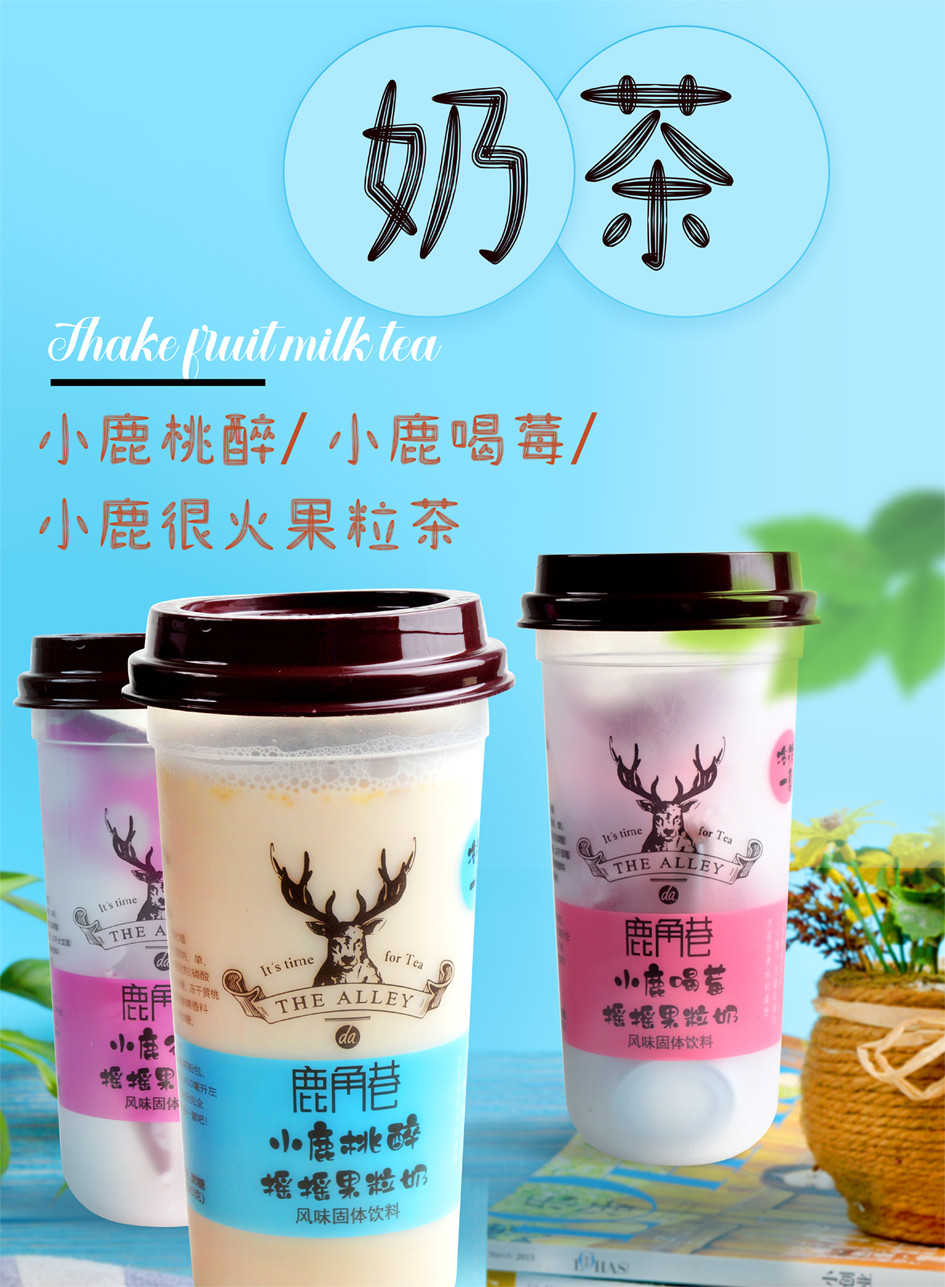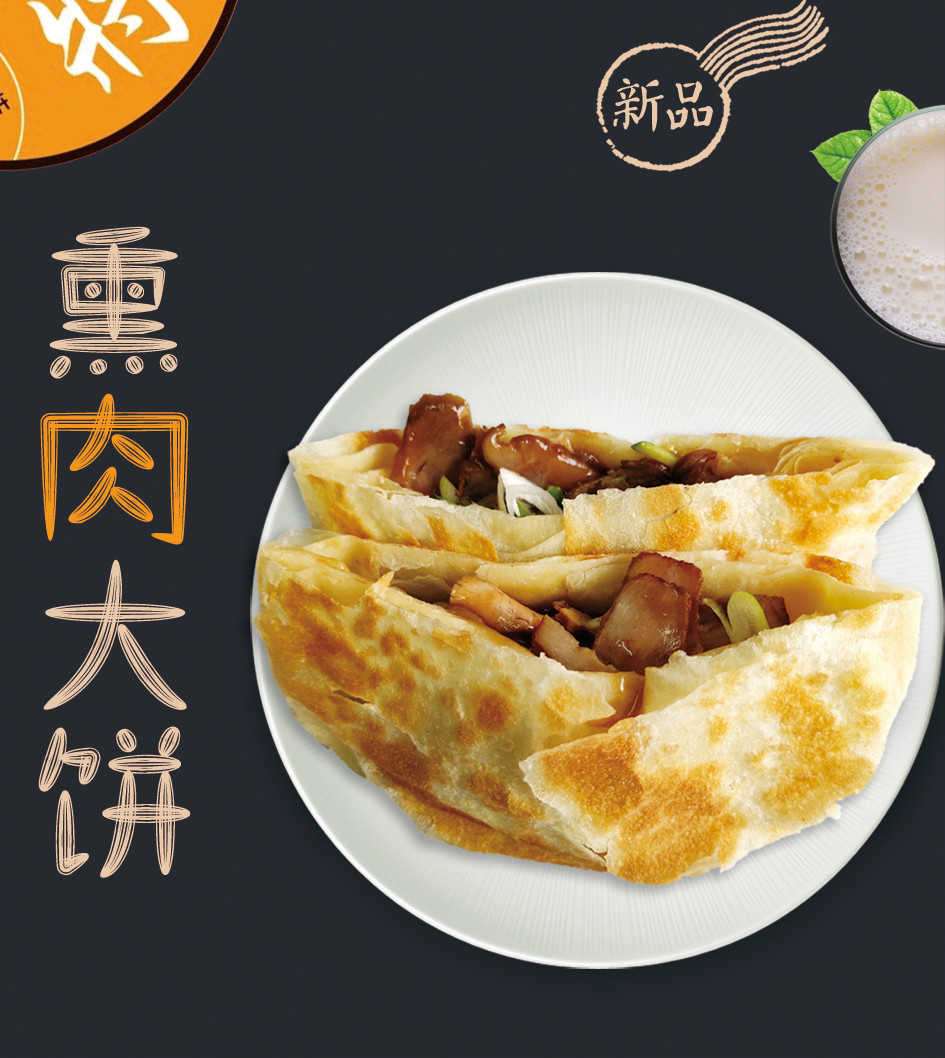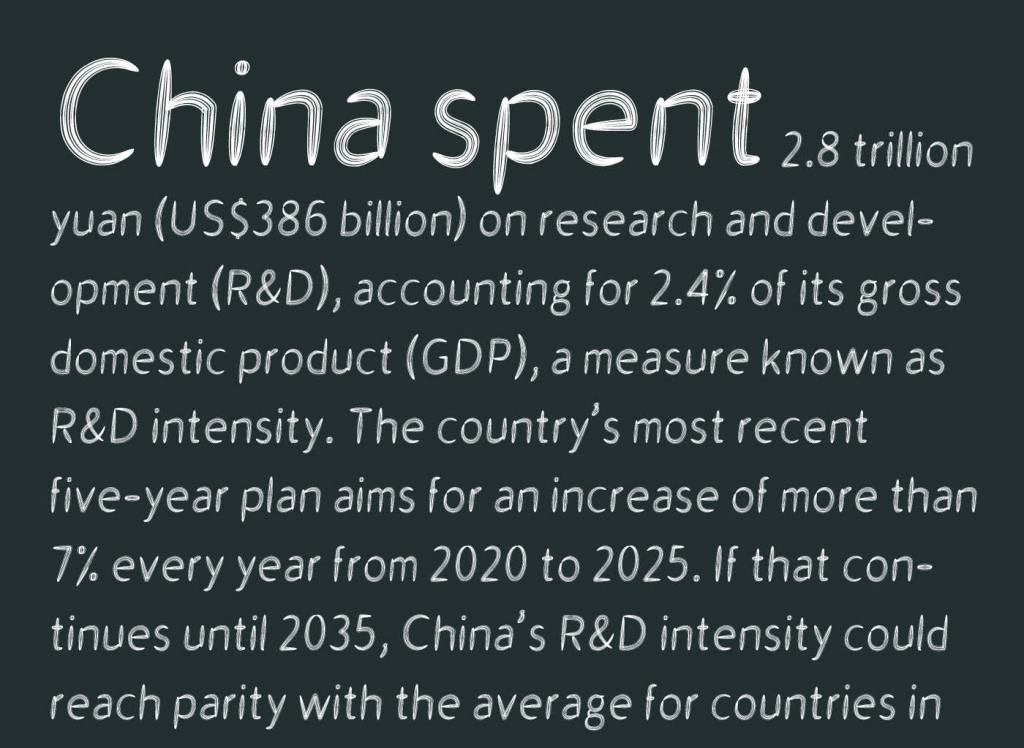
经过漫长的制作过程,山字瓜子体终于上线了。字库含6763个常用中文字以及若干英文常用字母和标点符号。由于笔画形似瓜子,故取名瓜子体。也因为所用笔画是常规字库的数倍,字库也比常规简单笔画的字库要大许多。
该字库适合广告设计中需要用到可爱或卡通的字体的时候,适合用大字体来显示,并不适合用小字(如四号等)来显示。
“山字瓜子体”是一款书写很新颖的字体,字体大方,适合各种设计作品使用!欢迎下载!